Bài viết này tổng hợp và phân tích chuyên sâu về các xu hướng nghệ thuật chữ nổi bật nhất trong năm 2026. Từ sự lên ngôi của các kiểu chữ động dựa trên AI đến sự quay trở lại của phong cách thô mộc, nội dung cung cấp cái nhìn toàn diện giúp các nhà thiết kế nắm bắt dòng chảy thẩm mỹ hiện đại, tối ưu hóa trải nghiệm người dùng và duy trì lợi thế cạnh tranh trong ngành sáng tạo.
Xu Hướng Typography 2026 Mà Designer Cần Biết Để Không Bị Lỗi Thời
Thế giới thiết kế đồ họa đang bước vào một kỷ nguyên mà ranh giới giữa tĩnh và động, giữa thực và ảo đang dần xóa nhòa. Typography không còn chỉ là công cụ để truyền tải thông tin bằng văn bản, mà đã trở thành linh hồn của bộ nhận diện thương hiệu. Trong năm 2026, chúng ta chứng kiến sự chuyển mình mạnh mẽ từ những font chữ tiêu chuẩn sang những hình thái biểu cảm đầy tính cá nhân hóa.
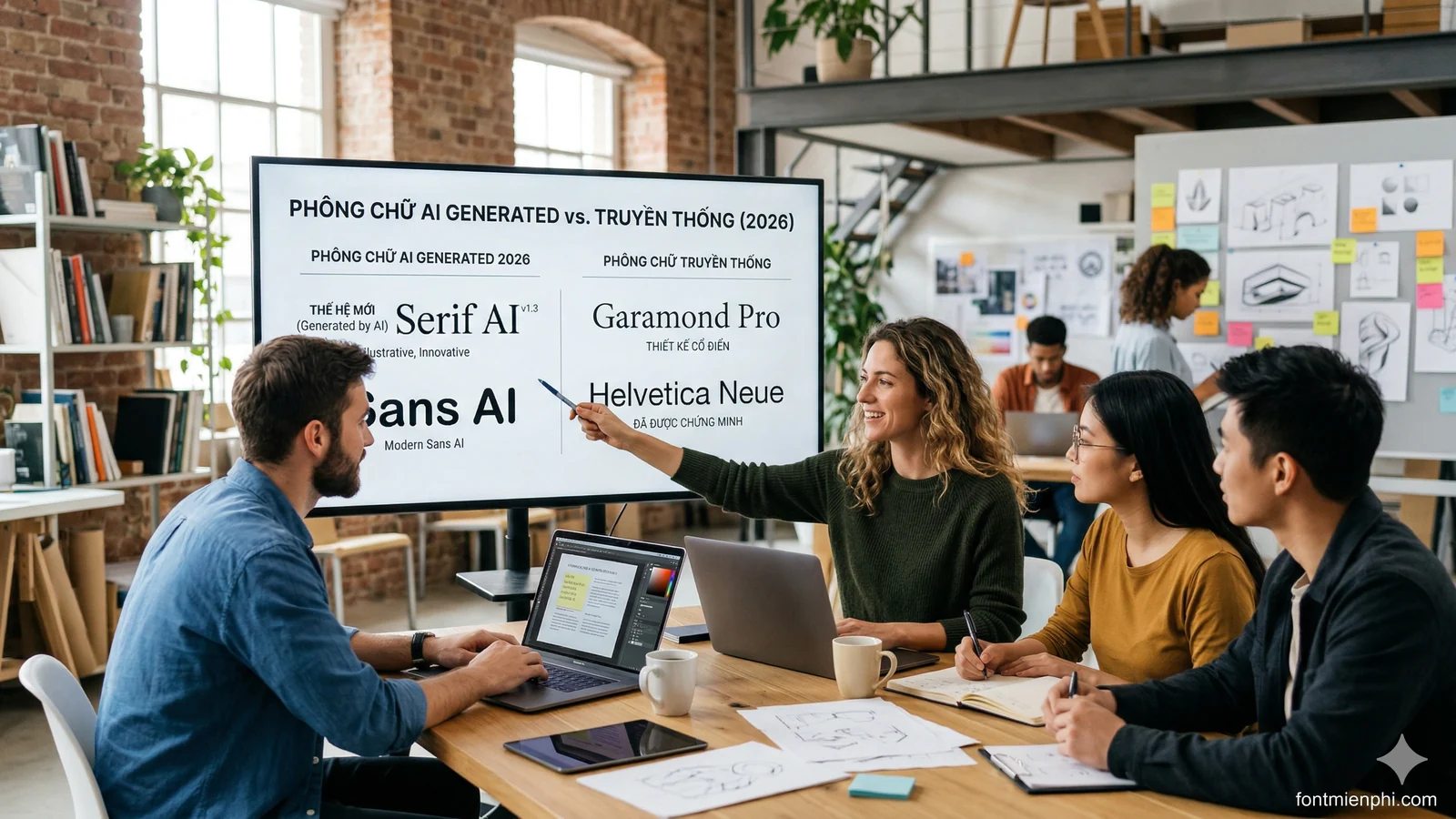
Sự Trỗi Dậy Của Typography Động Và Biến Đổi Theo Thời Gian Thực
Nếu như những năm trước, variable fonts chỉ mới dừng lại ở việc thay đổi trọng lượng hoặc chiều rộng, thì năm 2026 đánh dấu bước tiến xa hơn với khả năng tương tác dựa trên dữ liệu người dùng.
Typography phản ứng với hành vi: Các kiểu chữ trên nền tảng số có khả năng thay đổi hình dạng dựa trên tốc độ cuộn trang của người dùng hoặc âm thanh môi trường xung quanh.
Chữ cái có sự sống: Nhờ vào các thuật toán AI, chữ cái không còn đứng yên. Chúng có thể co giãn, uốn lượn như một sinh thể sống để thu hút sự chú ý vào các thông điệp quan trọng.
Tối ưu hóa khả năng đọc dựa trên thiết bị: Font chữ tự động điều chỉnh độ tương phản và khoảng cách ký tự để phù hợp với điều kiện ánh sáng và loại màn hình mà người xem đang sử dụng.
Phong Cách Maximalism Và Sự Phá Bỏ Các Quy Tắc Truyền Thống
Sau một thập kỷ thống trị của phong cách tối giản (Minimalism) với các font Sans Serif sạch sẽ nhưng đôi khi đơn điệu, năm 2026 chào đón sự trở lại của Maximalism đầy nổi loạn.
Kích thước cực đại: Các tiêu đề lớn chiếm trọn không gian thiết kế, đôi khi tràn ra ngoài mép ảnh để tạo cảm giác vô tận.
Sự kết hợp hỗn loạn nhưng có tính toán: Việc trộn lẫn từ ba đến năm kiểu chữ khác nhau trong cùng một bố cục trở thành một tuyên ngôn nghệ thuật, thể hiện sự đa dạng và phóng khoáng.
Chữ cái biến dạng có chủ đích: Các nhà thiết kế không ngần ngại kéo giãn, làm méo hoặc cắt cụt các phần của chữ cái để tạo ra hiệu ứng thị giác mạnh mẽ, miễn là vẫn giữ được khả năng nhận diện cơ bản.
Typography Sinh Học Và Cảm Hứng Từ Thiên Nhiên
Trong bối cảnh công nghệ AI bùng nổ, con người có xu hướng tìm về những giá trị nguyên bản và gần gũi. Typography sinh học (Biomorphic Typography) là lời giải cho sự cân bằng này.
Đường nét hữu cơ: Các font chữ mô phỏng hình dạng của rễ cây, dòng nước hoặc các tế bào sinh học mang lại cảm giác mềm mại và dễ chịu.
Màu sắc và kết cấu tự nhiên: Không chỉ là hình dáng, các bề mặt của chữ cái được lồng ghép các chất liệu như vân gỗ, đá tự nhiên hoặc hiệu ứng sương mù.
Sự không hoàn hảo có chủ đích: Khác với các font chữ kỹ thuật số sắc lẹm, xu hướng này ưu tiên các nét vẽ tay, các góc bo tròn không đều, tạo ra sự ấm áp và tính nhân văn trong thiết kế.
Sự Giao Thoa Giữa Cổ Điển Và Tương Lai – Neo-Heritage
Neo-Heritage là xu hướng lấy các giá trị di sản, các kiểu chữ từ thế kỷ trước và tái hiện chúng dưới lăng kính của công nghệ hiện đại.
Phục hưng Serif: Các kiểu chữ có chân đầy sang trọng của những thập niên 70, 80 được tinh chỉnh lại với đường nét thanh mảnh và sắc sảo hơn để phù hợp với màn hình Retina cao cấp.
Hiệu ứng Retro-Futurism: Kết hợp giữa cấu trúc chữ cổ điển với các hiệu ứng kỹ thuật số như ánh sáng neon, độ nhiễu điện tử (glitch) hoặc đổ bóng đa chiều.
Văn hóa bản địa: Việc sử dụng các yếu tố thư pháp hoặc ký tự mang đậm dấu ấn văn hóa địa phương vào trong thiết kế hiện đại đang trở thành một cách để các thương hiệu khẳng định nguồn gốc và sự độc đáo.
Ứng Dụng Chữ 3D Và Không Gian Đa Chiều
Với sự phổ biến của kính thực tế ảo (VR) và thực tế tăng cường (AR), typography 2026 không còn nằm trên một mặt phẳng.
Chiều sâu thị giác: Chữ cái được thiết kế với khối lượng và trọng lượng thực tế, có bóng đổ và khả năng phản chiếu ánh sáng như vật thể thật.
Typography lơ lửng: Trong không gian số, chữ có thể trôi nổi và thay đổi góc nhìn tùy theo vị trí của người xem, tạo ra trải nghiệm đọc mang tính nhập vai.
Vật liệu kỹ thuật số: Các nhà thiết kế sử dụng chất liệu như nhựa lỏng, kim loại nóng chảy hoặc thủy tinh để tạo hình cho chữ cái, mang lại cảm giác cực kỳ hiện đại và sang trọng.
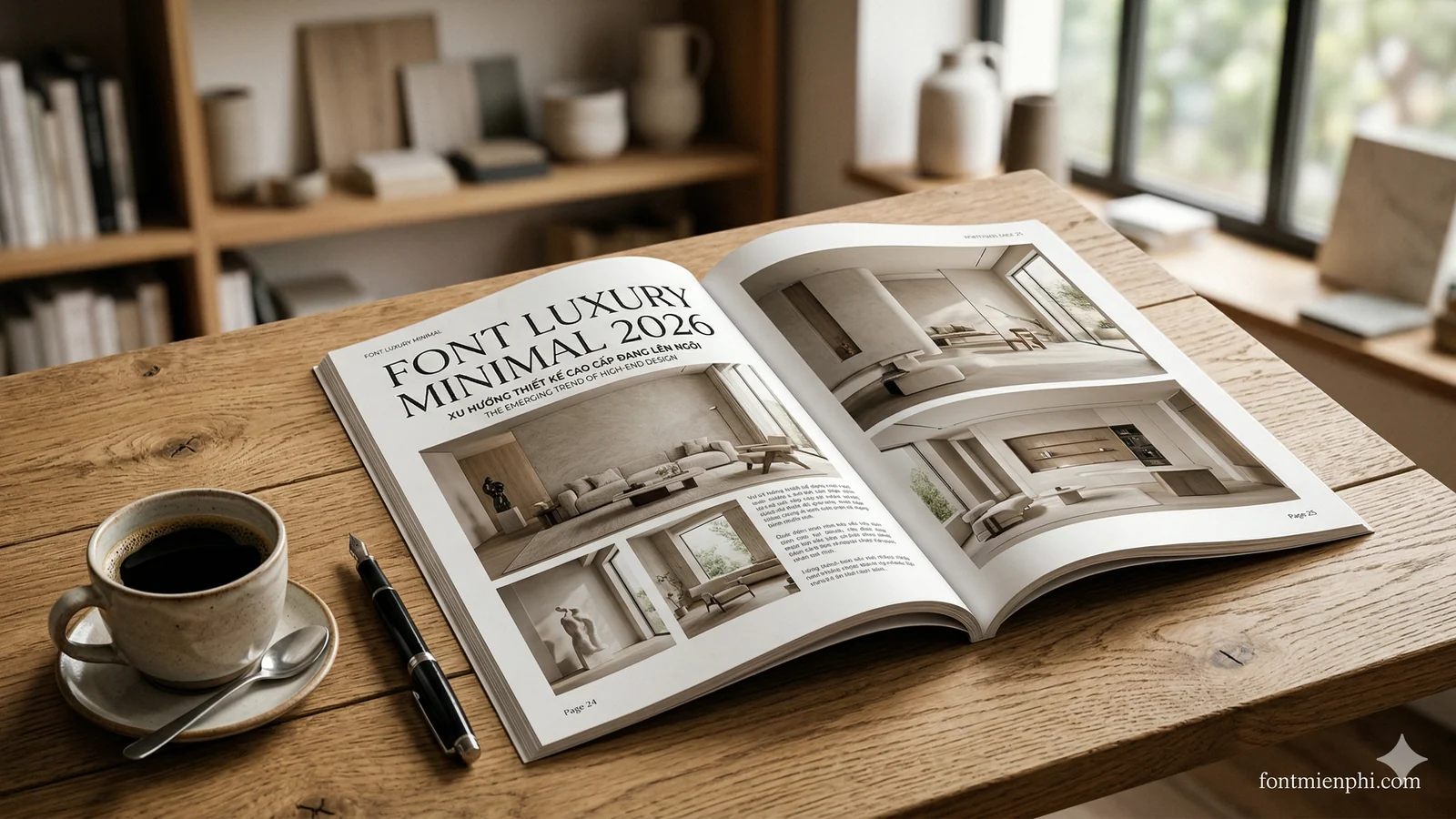
Khái niệm bền vững không chỉ áp dụng cho vật liệu mà còn lan tỏa sang cả thiết kế đồ họa, đặc biệt là trong việc lựa chọn kiểu chữ để tiết kiệm tài nguyên.
Font chữ tiết kiệm mực: Các kiểu chữ được thiết kế với các lỗ li ti bên trong hoặc nét chữ mảnh hơn để giảm lượng mực in mà vẫn đảm bảo độ sắc nét khi nhìn bằng mắt thường.
Typography không chỉ là những ký tự vô hồn, chúng là tiếng nói của thiết kế. Khi công nghệ tiếp tục tiến xa, cách chúng ta tương tác với chữ cái sẽ còn nhiều thay đổi thú vị hơn nữa. Designer cần giữ một tâm thế mở, sẵn sàng học hỏi các công cụ mới như AI và các nền tảng thực tế ảo để biến những con chữ thành những trải nghiệm thị giác khó quên. Sự tinh tế trong cách chọn font, sự dũng cảm trong cách dàn trang và sự nhạy bén với xu hướng sẽ là những chìa khóa vàng để tạo nên những sản phẩm thiết kế xuất sắc trong năm 2026.